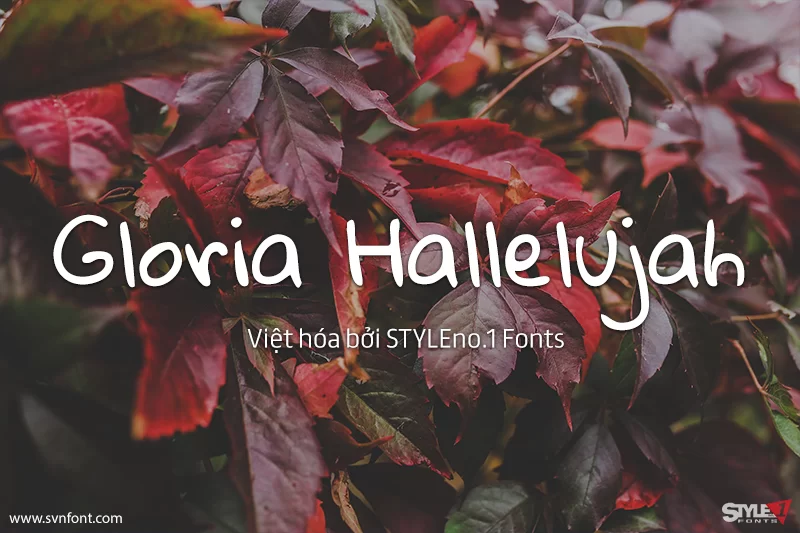
Phông chữ này dựa trên chữ viết tay của một học sinh trung học Hàn Quốc. Đó là niềm vui và nhắc nhở tôi về một phong cách truyện tranh. Nó trông tuyệt vời và dễ đọc.
Nhà thiết kế: Kimberly Geswein
Nhà phát hành: Principal design
Việt hóa: STYLEno.1 Fonts